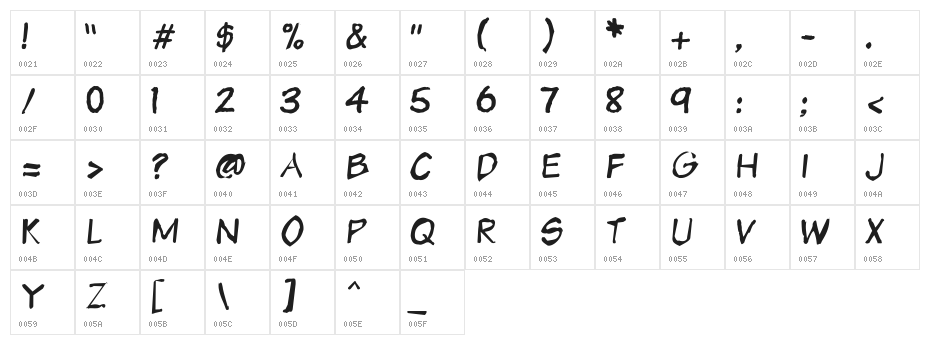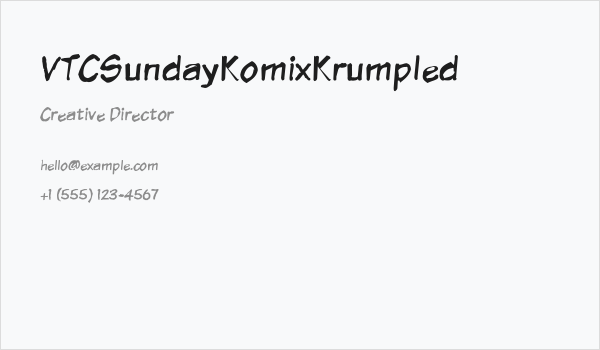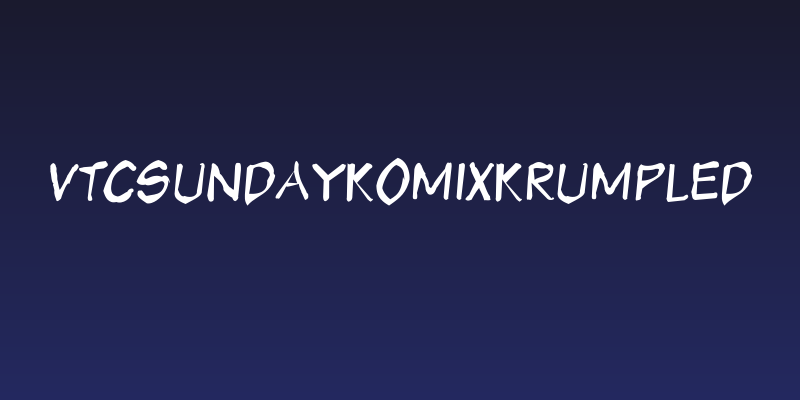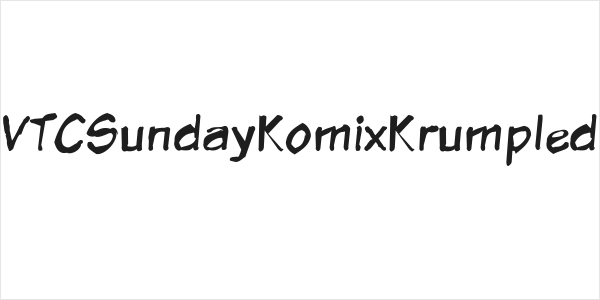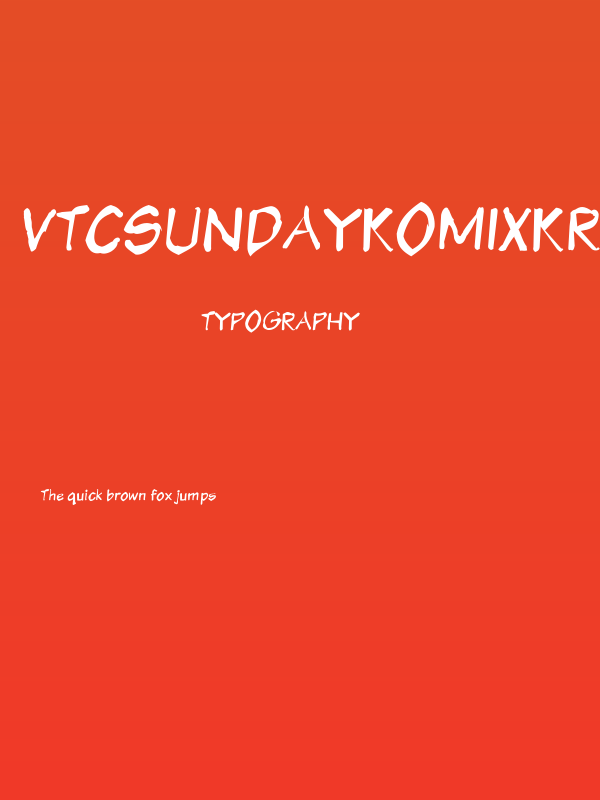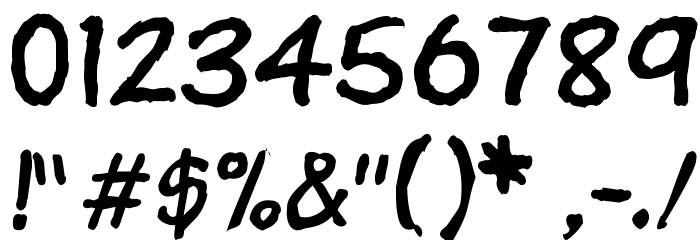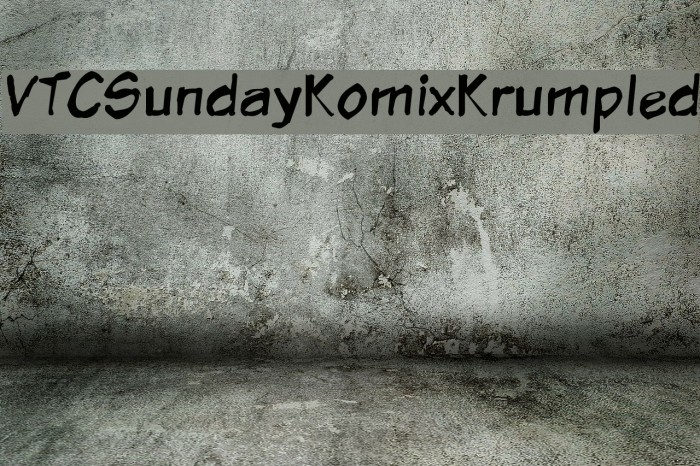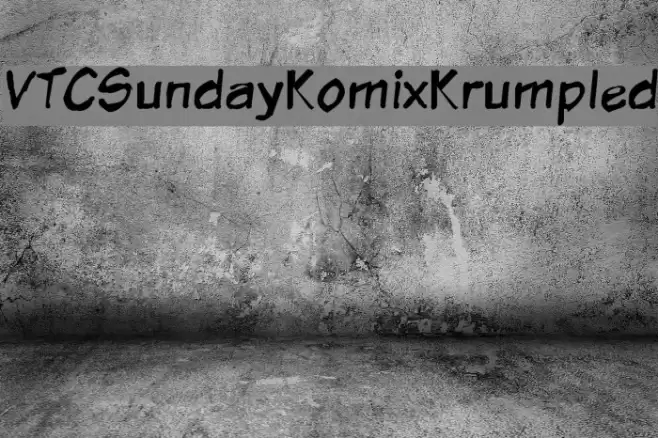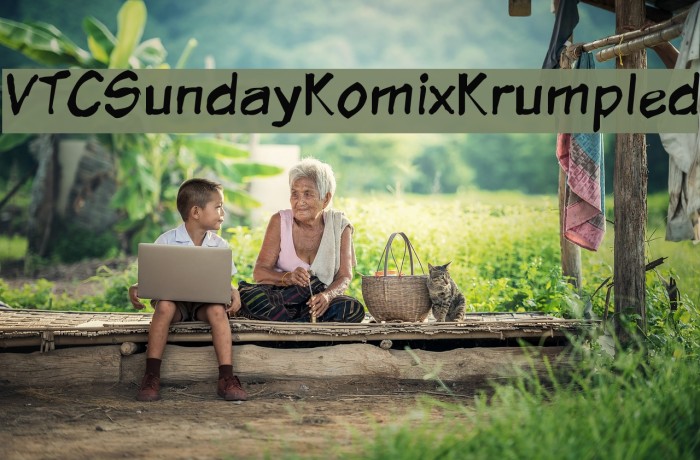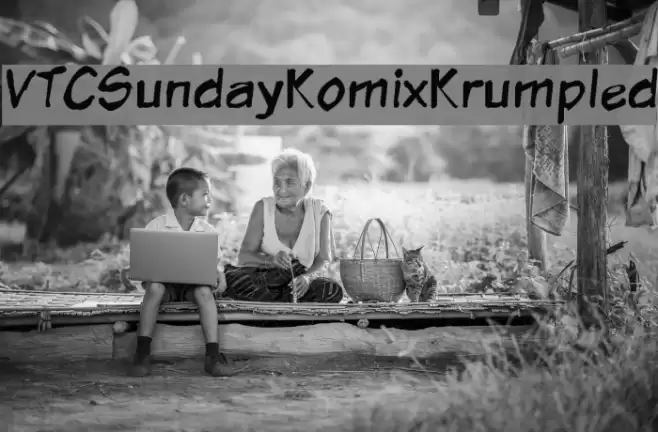
VTCSundayKomixKrumpled Font
| Gesamtstil | Playful, Comic |
| Vorgeschlagene Projekte | Ideal for comic books, children's books, posters, and playful branding materials. |